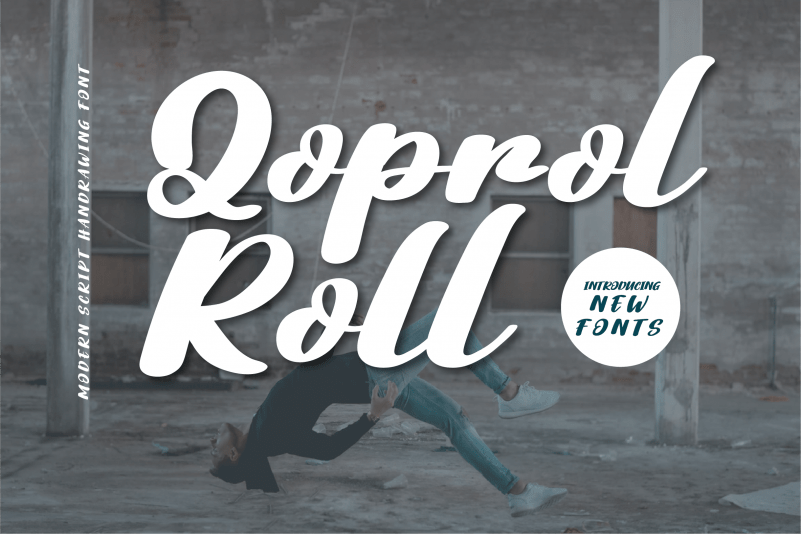
Qoprol Roll Script Font – Fonte Grátis
Qoprol Roll Script Font
A fonte Qoprol Roll Script é uma graça elegante que combina a fluididade do script com a facilidade de escrita de uma abrangente serifada. Inspirada no estilo de escrita oriental, esta fonte oferece um toque refinado e criativo para projetos digitais de design gráfico, desde letras em cartazes até desenhos em vídeos. Crie experiências memoráveis com a Qoprol Roll Script Font: ela é perfeita para designers que buscam uma alternativa versátil à sua fonte de trabalho atual. Com seu designer twinletter, estamos felizes por oferecer esta peça única e elegante do mundo da tipografia.